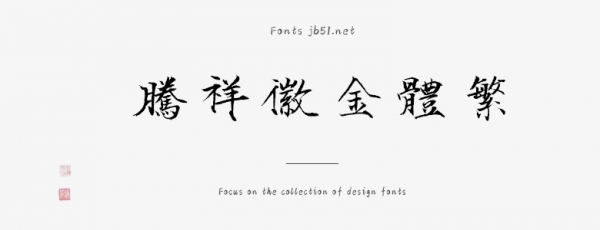
騰祥徽金體繁是一款不錯的藝術(shù)字體,由騰祥字庫出品,字體橫筆畫收筆處帶勾、豎筆畫收筆處帶點、撇捺飄逸優(yōu)雅、字形結(jié)構(gòu)端正挺拔,適合應(yīng)用于藝術(shù)設(shè)計、平面宣傳設(shè)計、網(wǎng)頁設(shè)計,書法字帖等領(lǐng)域,需要的朋友可以前來本站下載。
此款字為書法體。以宋徽宗的手跡瘦金書作為創(chuàng)作藍本,保留瘦金體特點:橫筆畫收筆處帶勾、豎筆畫收筆處帶點、撇捺飄逸優(yōu)雅、字形結(jié)構(gòu)端正挺拔。其中,又融入作者對瘦金體的深度領(lǐng)悟形成徽金楷書獨特風格。特點鮮明,有勁道,有風骨。本作品可適用于印刷出版、包裝設(shè)計、廣告設(shè)計、網(wǎng)頁設(shè)計、屏幕顯示等。